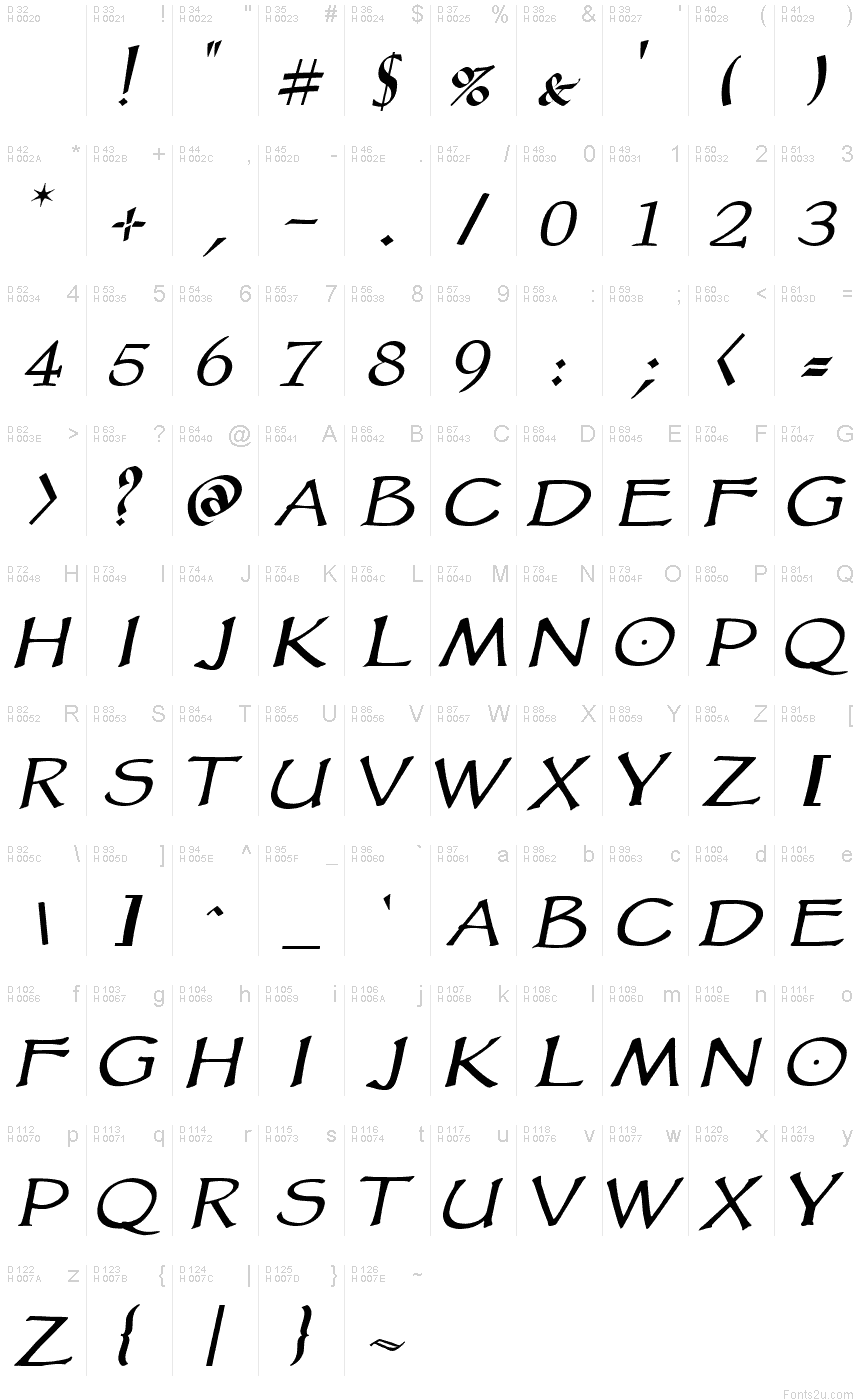
VTC Goblin Hand Italic di VTC Vigilante Typeface Corporation è un font display gratuito in stile retro, composto da sole maiuscole, con un'inclinazione furba e fiabesca. Le lettere sembrano disegnate a mano e quasi teatrali, con giunzioni strette, estremità ricurve e un ritmo vivace che conferisce al testo un sapore "da goblin", come quello di vecchi manifesti, invece della solita pulizia formale.
Si adatta perfettamente a volantini di Halloween, copertine di libri fantasy, titoli di giochi, menu per locali a tema e loghi originali che necessitano di un po' di malizia senza trasformarsi in una scritta troppo stravagante. Dato che le maiuscole si inclinano e si agganciano in modo così animato, è ottima anche per titoli brevi, monogrammi e capilettera che richiedono un tocco di incanto vintage.